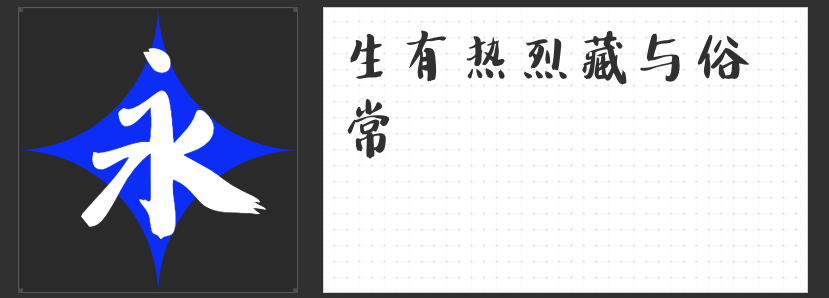
毛笔字的魅力:四款精品毛笔字体推荐
毛笔字,作为中华文明的瑰宝之一,不仅承载着深厚的历史文化底蕴,也因其独特的艺术美感而备受现代设计师们的青睐。随着数字化时代的到来,越来越多的毛笔字库被开发出来,让设计师们能够在各类设计项目中轻松地融入这一传统艺术形式。以下是四款极具特色的毛笔字体推荐,它们各具风格,适用于不同的设计场景。
云书法家韩进水魏碑简繁 - 这款字体基于魏碑的经典风格,融合了书法家韩进水先生的个人特色。其笔画流畅有力,结构严谨,非常适合用于书籍封面设计、文化宣传资料以及传统节日相关的装饰性文字排版。无论是打造一份具有浓厚古典韵味的邀请函,还是设计一款彰显文化底蕴的LOGO,云书法家韩进水魏碑简繁都能够为你的作品增添一抹独特的东方魅力。
造字侠陈坤风行简繁 - 以其飘逸洒脱的笔触著称,字形灵动而不失稳重,特别适合于表现轻松愉悦、自由自在的设计主题。无论是为旅游宣传册添加一抹清新自然的气息,还是为品牌故事讲述提供更具亲和力的文字表达方式,这款字体都能让你的设计作品更加贴近人情味,传递出积极向上的情感共鸣。
云书法墨迹建刚楚楷体 - 这款字体继承了楷书方正典雅的传统,同时融入了现代审美观感,展现出一种简洁大方而又不失细节精致的风格。它尤其适用于正式文件、企业报告或学术出版物等领域,能够使整体文档呈现出专业严谨的态度,同时也透露出一丝古典雅致的美感。
造字侠今朝醉简 - 这款字体以其豪放不羁、挥洒自如的书写特点脱颖而出,给人以强烈视觉冲击力的同时,也传递出一种洒脱不羁的精神内核。此款字体非常适合用于海报设计、广告标语或是社交媒体上的创意文案等场合,能够迅速吸引观众注意力,并留下深刻印象。
通过上述四款各具特色的毛笔字体,设计师们可以更加灵活地将传统书法艺术与现代设计理念相结合,创造出既有深度又具创新性的作品。无论是追求古典美感还是现代潮流,这些字体都能为你带来意想不到的设计灵感与视觉享受。